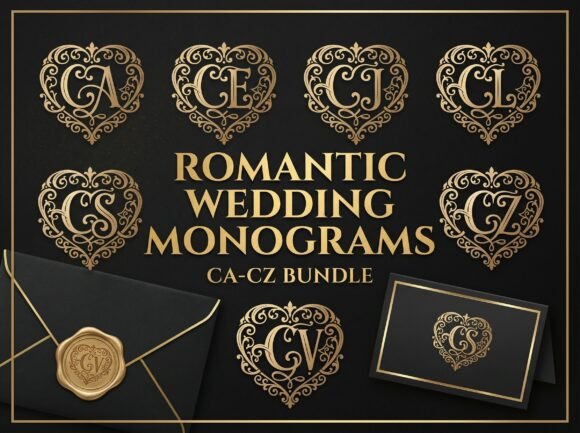
26 Romantic Wedding Monogram CA-CZ
Om du letar efter högkvalitativa tillgångar som 26 Romantic Wedding Monogram CA-CZ, är detta premiumpaket ett fantastiskt val för dina kreativa projekt.